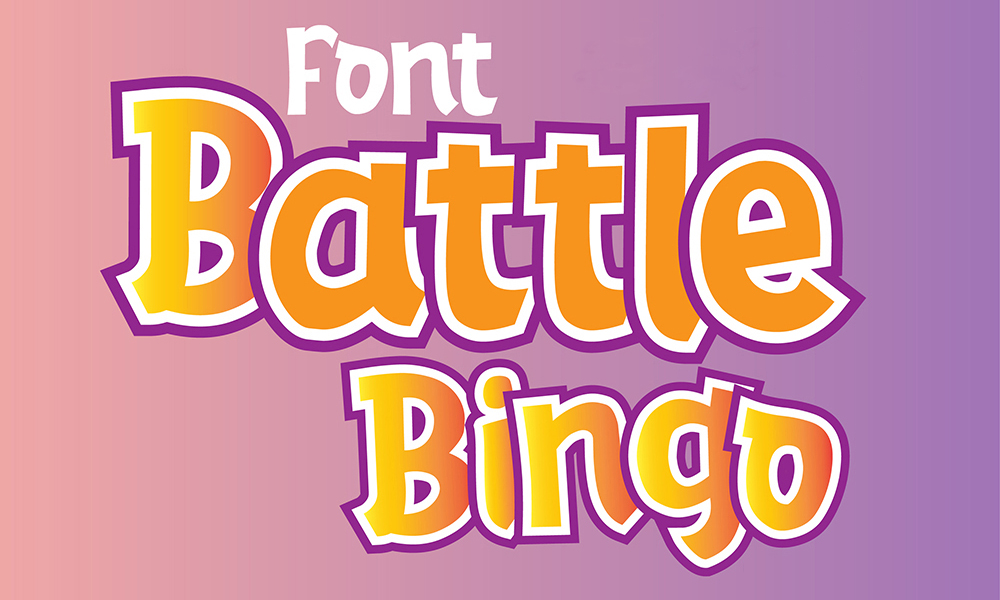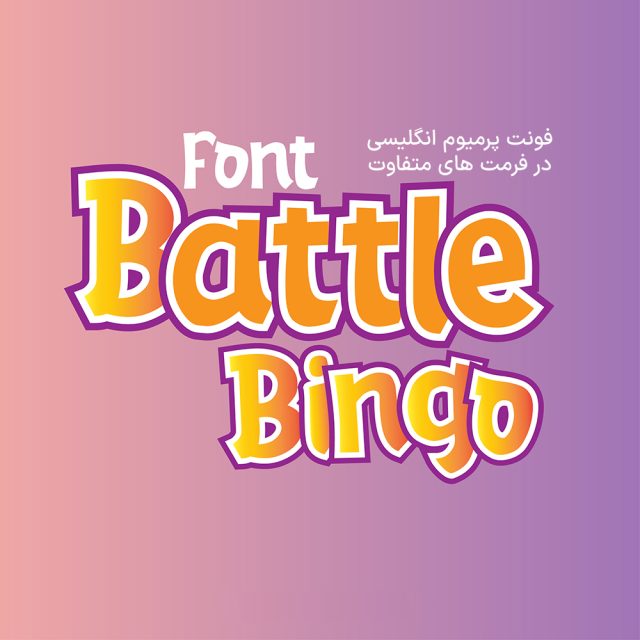
دانلود فونت انگلیسی Battle Bingo Font
فونت پرمیوم و انگلیسی Battle Bingo یک فونت بازیگوش و فانتزی است. این فونت با سبک دستنویس آزاد و با استفاده از ماژیک ساخته شده است.…
فونت پرمیوم و انگلیسی Battle Bingo یک فونت بازیگوش و فانتزی است. این فونت با سبک دستنویس آزاد و با استفاده از ماژیک ساخته شده است. این فونت به تمام طرحهای شما جلوهای شیک و شاد میدهد. شما میتوانید از این فونت برای لوگو، لباس کودکان، دعوتنامه، پوستر، طراحی دوستانه، طراحی سرگرمکننده، جلد کتاب، پوستر ماجراجویی، پوستر تبلیغاتی و هرگونه فونت بامزه و خندهدار دیگر استفاده کنید.
مزایای استفاده از فونت لاتین Battle Bingo چیست؟